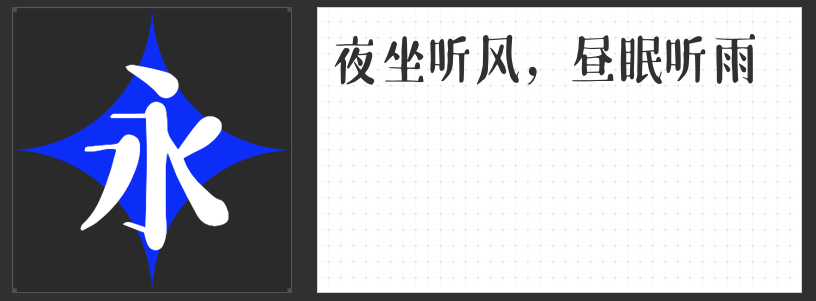
海报设计字体精选:四款风格化字体,解锁视觉创意新维度
海报是品牌与观众对话的视觉窗口,字体作为核心元素之一,直接影响信息传递的精准度与艺术感染力。以下四款字体以独特的设计语言与结构美学,为海报设计注入专业质感与风格张力。
一、励字超级勇士简 常规
这款黑体以严谨的几何结构为骨架,却通过柔和的笔画弧度打破传统黑体的生硬感。横竖笔画采用微曲处理,转折处过渡自然,既保留黑体的理性秩序,又赋予文字温暖的人文气质。中宫适度收紧的设计,让长文本排版更显紧凑有序,适合科技、时尚类海报中需要兼顾专业性与亲和力的场景,传递理性与温度并存的视觉语言。
二、励字开拓者简 特黑
以直线为绝对主导的开拓者特黑,通过横平竖直的笔画构建出如建筑般稳固的视觉框架。去钩处理与棱角分明的转折强化了字体的未来感,内部均匀的几何留白则赋予文字呼吸感。作为标题字体时,其强烈的视觉冲击力可瞬间抓住观众注意力;搭配家族系列中其他字重作为正文,又能形成层次分明的排版体系,适用于工业设计、运动品牌等强调力量感与现代性的海报场景。
三、高手庆科竞速体 常规
瘦长的字型与紧凑的中宫,让竞速体天生具备向前冲刺的动态势能。横竖笔画视觉等粗的设计,配合去钩后内收的斜切处理,既保持了文字的简洁性,又通过笔画方向的暗示强化速度感。四档字重覆盖从轻盈到厚重的全场景需求,无论是作为主标题的锐利表达,还是作为副标题的层次递进,都能以理性的秩序感传递出充满张力的视觉叙事。
四、高手庆科自由宋 常规
这款宋体以手写感为基调,通过圆润的笔画与灵动的装饰角打破传统宋体的严肃感。横细竖粗的经典结构中,横画末端的圆形装饰与细长上挑的钩笔画,为文字注入俏皮的视觉韵律。西文字符延续圆润设计语言,实现中英文的无缝风格统一。适合文化、艺术类海报中需要营造轻松氛围或传递人文温度的场景,让传统宋体焕发出现代生命力。
从理性几何到动态韵律,从力量感到亲和力,这四款字体以差异化的设计语言,为海报设计提供了丰富的风格选择。精准把握字体气质与品牌调性的契合点,方能让文字成为海报中最具说服力的视觉符号。